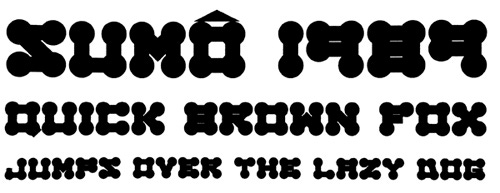
Tipo Aquilo #50 – Tipos brasileiros da era do bit lascado
Esta edição é baseada nos livros O Design Brasileiro de Tipos Digitais, de Ricardo Esteves, e Fontes Digitais Brasileiras: de 1989 a 2001, organizado por Priscila Farias e Gustavo Piqueira.
Em algumas edições do TA, as histórias mostram com certa clareza os atrasos que o Brasil teve em relação à tipografia. Dois momentos cruciais foram a proibição de atividades manufatureiras no período colonial e a reserva de mercado de produtos de tecnologia, imposta durante a ditadura militar. Nestes dois momentos, perdemos o bonde de transformações importantes que a produção tipográfica vivia no mundo. Especialmente nos anos 1970 e 1980, em que a tipografia digital chegava a seus primeiros formatos de criação e distribuição comercial, mas o Brasil mal tinha computadores para abastecer um mercado latente, e uma redação ou outra tinha o luxo do desktop publishing.
Isso parece triste, a princípio; no entanto, os anos seguintes foram marcados por uma intensa corrida contra o atraso que teve dois resultados importantes. Primeiro, uma produção de fontes sui generis, que olhava para o que vinha de fora mas também refletia sobre as letras abertas por aqui. Segundo, a formação de uma comunidade ativa, pensante e producente de designers, professores e pesquisadores brasileiros que criaram fontes, trocaram conhecimento, ministraram workshops, palestras e conferências, e disseminaram a palavra da tipografia para que ela alcançasse o nível de excelência e reconhecimento internacional que várias fontes brasileiras têm no mercado. A edição de hoje é uma pequena reverência a esse momento da tipografia brasileira, movida a disquetes, internet, cerveja e muita experimentação.
Para entender como essa corrida começou, precisamos voltar a 1989. Nessa época, o Muro de Berlim foi abaixo, o Macintosh completava cinco anos no mercado e aplicativos como o Fontstudio e o Fontographer ofereciam um ambiente poderoso para criar fontes vetoriais. No Brasil, a transição lenta, gradual e segura (risos) permitiu aos brasileiros escolherem um presidente pela primeira vez em 25 anos, e algumas iniciativas de criação de fontes em solo brasileiro compreendiam experimentos de reproduzir fontes tradicionais para uso em legendas, e a criação de letras derivadas de logotipos feitas pelo uruguaio Eduardo Bacigalupo.
A reserva de mercado de tecnologia acabaria apenas dois anos mais tarde, mas com jeitinho, um computador ou outro chegava a escritórios e casas brasileiras. Num deles, instalado na redação da Folha de S. Paulo, o ilustrador Tony de Marco deu vida à primeira fonte digital brasileira com desenho inédito de que existe registro, a Sumô. Tony desenvolveu outras fontes digitais nos anos seguintes, inaugurando um período de desenvolvimento de tipos majoritariamente experimentais, que seguiam a tendência do design desconstruído de designers como David Carson. A falta de livros e materiais didáticos sobre tipografia fez com que as primeiras fontes digitais fossem criadas desbravando os recursos das ferramentas existentes por conta própria.
Essa primeira fase da produção tipográfica brasileira teve uma explosão entre 1997 e 2001, conforme mais lares e escritórios informatizados ganhavam acesso à Internet. Até que a conexão caísse por um modem queimado ou alguém tentando usar a linha telefônica, a Internet era um espaço aberto para a colaboração e troca de conhecimento, experiências, e até das próprias fontes e ferramentas de criação, como o recém-criado FontLab Studio. A possibilidade de publicar e vender fontes autorais foi outro motivador para as dezenas de fontes produzidas por designers independentes e pequenos estúdios, como o Tipos do aCASO, Fontes Carambola, Subvertaipe, Tipos Maléficos, Gemada Tipográfica, Elesbão e Haroldinho, Tipograma, entre outros.
As fontes corporativas das empresas Graal, TransBrasil e Ultragaz, projetadas por Fernanda Martins, são exceções a esse período experimental e inauguram a lista de fontes feitas sob medida por designers brasileiros. No entanto, a maioria das fontes brasileiras desse período mostravam formas que colocavam a legibilidade à prova, exploravam as possibilidades do desenho vetorial, consumiam funcionalidades como o live tracing, simulavam a escrita manual, a sujeira da impressão no desenho tipográfico, e até usavam fontes clássicas como insumos para produzir novos vetores. Dessa forma, designers usavam a tipografia não apenas como um recurso a favor da desconstrução de projetos gráficos e das noções tidas como canônicas no design gráfico, mas como uma forma de expressão per se. Fontes como a Gema e a Underscript, de Claudio Rocha, a LowTech e a Quadrada, de Priscila Farias, foram as primeiras a serem revendidas internacionalmente, por meio da distribuidora T-26.
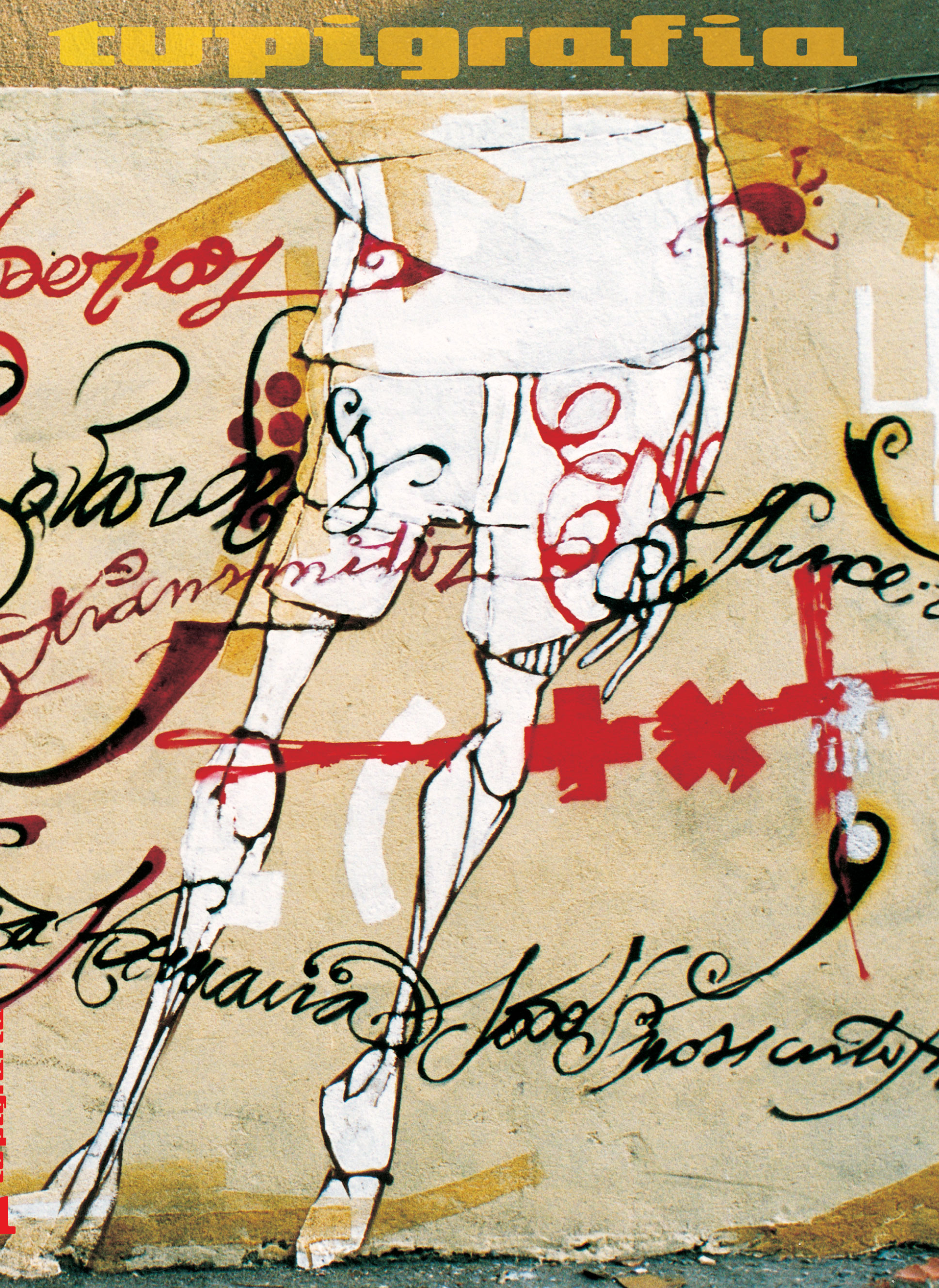
A virada do século inaugurou uma fase de amadurecimento da produção tipográfica no Brasil, uma passagem do bit lascado para o bit polido da tipografia digital. Três marcos inaugurais dessa nova fase foram: a exposição “Tipografia Brasilis”, realizada em São Paulo de 2000 a 2002 e promovida pela FAAP; o lançamento da revista “Tupigrafia” no ano 2000, de Claudio Rocha e Tony de Marco; e a família tipográfica Houaiss, desenvolvida pelo designer e professor Rodolfo Capeto e lançada em 2001 para a versão impressa do Dicionário Houaiss da Língua Portuguesa. Esses três marcos referem-se tanto à guinada que os desenhos dos tipos brasileiros teriam daquele ponto em diante, quanto às atividades de promoção e difusão de conhecimento sobre tipografia no Brasil.
A Tipografia Brasilis, em seus três anos, reuniu diversos trabalhos de tipografia experimental e letreiramento, celebrando a safra de type designers brasileiros, ajudando a inserir tipografia como uma nova categoria na Bienal de Design Gráfico da ADG, e trazendo em sua última edição um workshop do designer de tipos argentino Ruben Fontana. Outros workshops promovidos na Bienal de Design Gráfico da ADG de 2002, com o designer inglês Bruno Maag, e em eventos locais ajudaram a espalhar conhecimentos e práticas da criação de fontes para novos interessados. Nessa década, nasceram também os primeiros congressos de tipografia feitos no Brasil, como o DNA Tipográfico em 2003 e 2005 (organizado pela Tupigrafia e Senac/SP); o Letras Latinas, depois rebatizado de Tipos Latinos, reunindo tipógrafos de toda a América Latina; e o DiaTipo, que acontece desde 2008.
Além do conhecimento trazido por type designers estrangeiros em workshops, a partir dessa década, vários brasileiros tornaram-se alunos de prestigiadas especializações em tipografia em países como Argentina, Espanha, Países Baixos e Reino Unido; as conferências da ATypI também passaram a ter mais brasileiros entre seus participantes. As fontes produzidas por brasileiros alinham-se mais com o mundo em termos de estilo e de excelência, com várias fontes para títulos e textos alcançando projeção internacional. A presença dessas fontes em distribuidoras famosas, como a FontSmith e a Dalton Maag, soma-se a um número crescente de fontes vendidas na plataforma MyFonts, criada pela Bitstream (hoje, da Monotype) para disponibilizar fontes de estúdios e foundries independentes. O volume anual de fontes inéditas publicadas por brasileiros na plataforma passa de três em 2002 para 109 em 2009, atingindo o pico de 214 novas fontes em 2007.
Assim como a quantidade de fontes, também cresceu a literatura sobre tipografia em língua portuguesa, graças ao trabalho de autoria e tradução de vários pesquisadores brasileiros. Fico até feliz por serem tantos livros e autores que seja inviável citá-los aqui sem penosas omissões (mea culpa aqui): traduções de André Stolarski e Luciano Cardinali para livros importantes, e as obras de Priscila Farias, Leonardo Buggy, Claudio Rocha, entre outros, ajudaram a dar nomes às convenções tipográficas consolidadas no exterior, espalhar a palavra da tipografia e dar mais referências bibliográficas para os trabalhos acadêmicos de novos alunos.